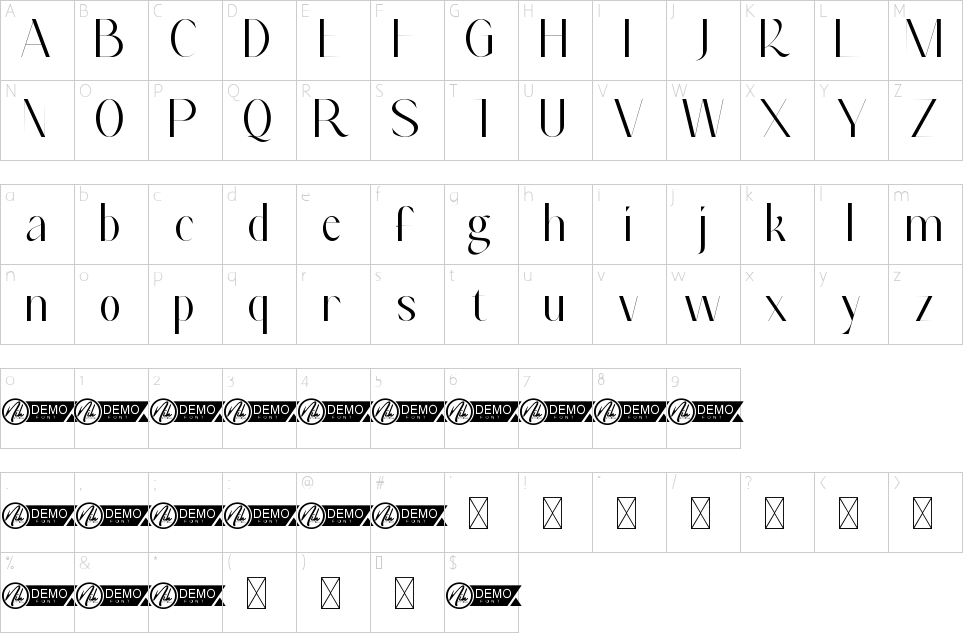
Arieva Nadire é uma fonte gratuita que oferece uma aparência gráfica atraente e envolvente. Sua criadora, NihStudio, apresenta Arieva Nadire para quem busca uma fonte de qualidade sem precisar investir em um sistema de licenciamento. Com apenas 164 downloads, Arieva Nadire já conquistou o coração de criadores de projetos digitais que valorizam a simplicidade e a elegância em seus designs. Seja para textos formais ou legais, ou para gráficos e design gráfico, Arieva Nadire não decepciona. Com uma aparência natural e naturalmente agradável, ela é perfeita para designers que desejam oferecer ao seu público uma experiência visual confortável e envolvente. Se você está procurando por uma fonte gratuita que não comprometa a qualidade, Arieva Nadire é uma opção perfeita.